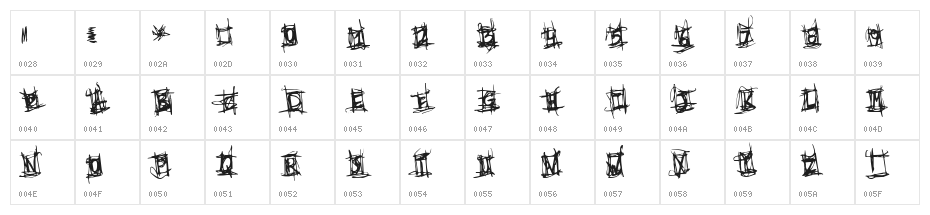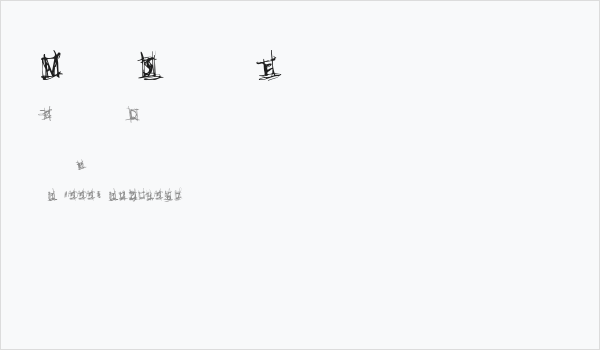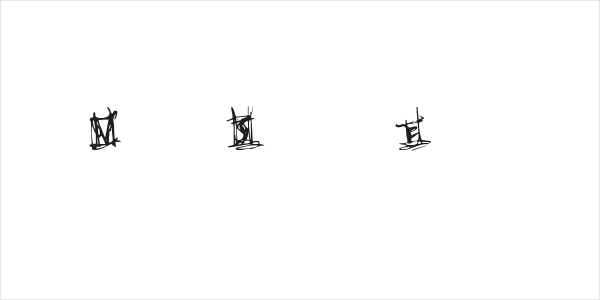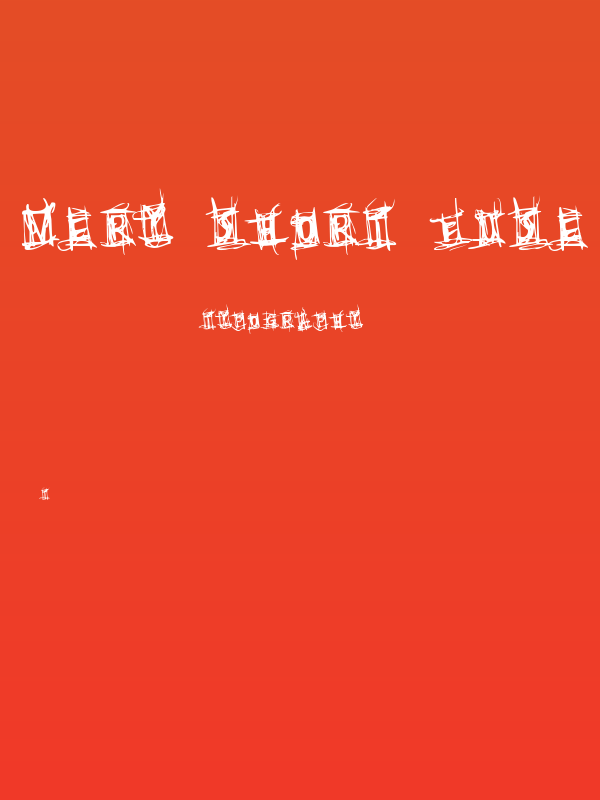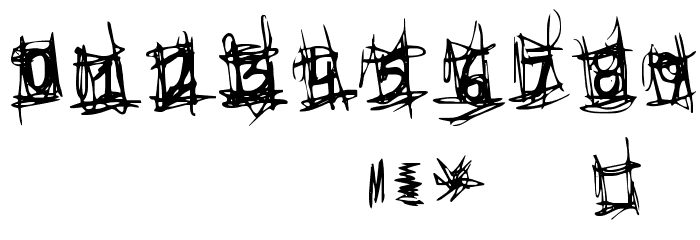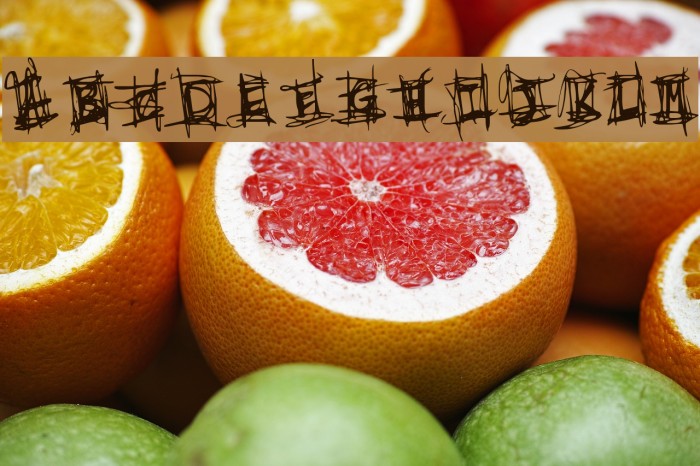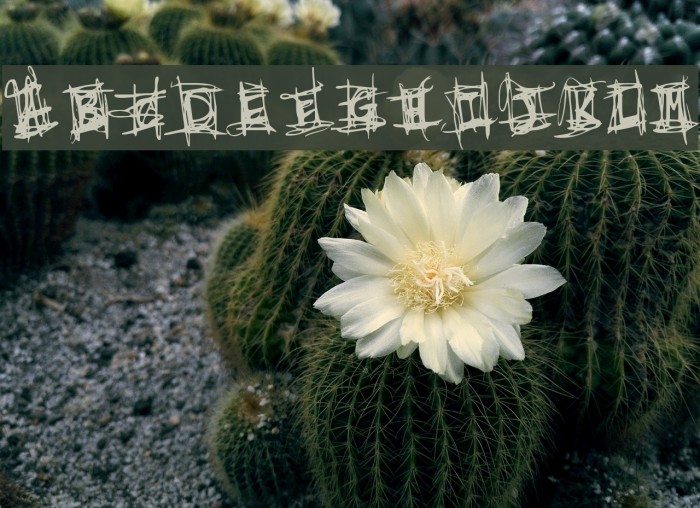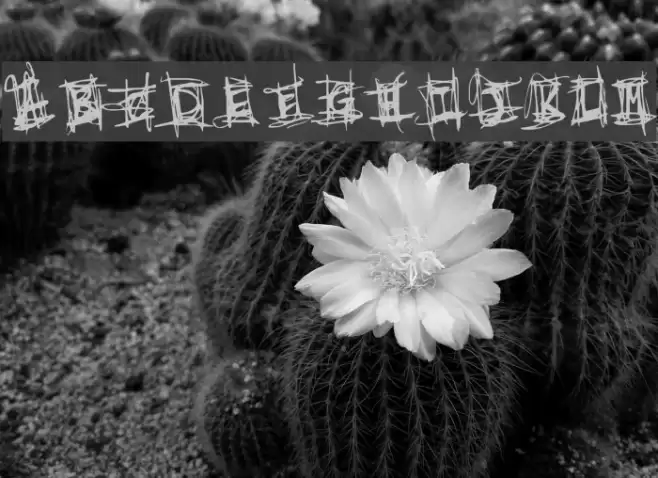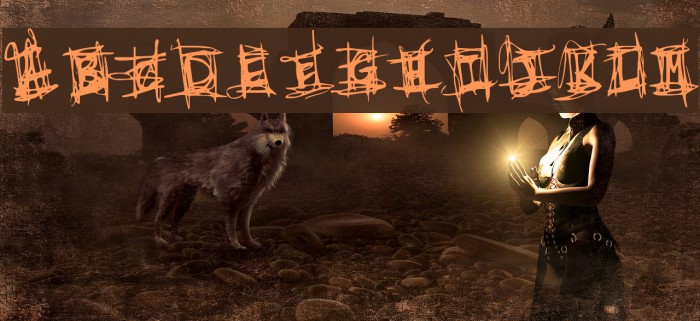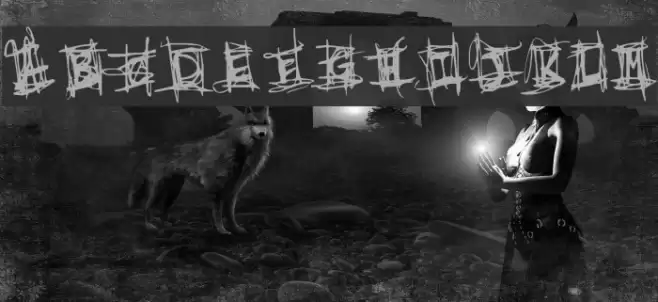
Very Short Fuse Font
| Общий стиль | Modern, Artistic |
| Область применения | Logos, Posters, Album Covers |
| Рекомендуемые проекты | Ideal for edgy graphic design projects, album covers, street art-inspired posters, or any creative work that seeks to convey a sense of rebellion or artistic freedom. |